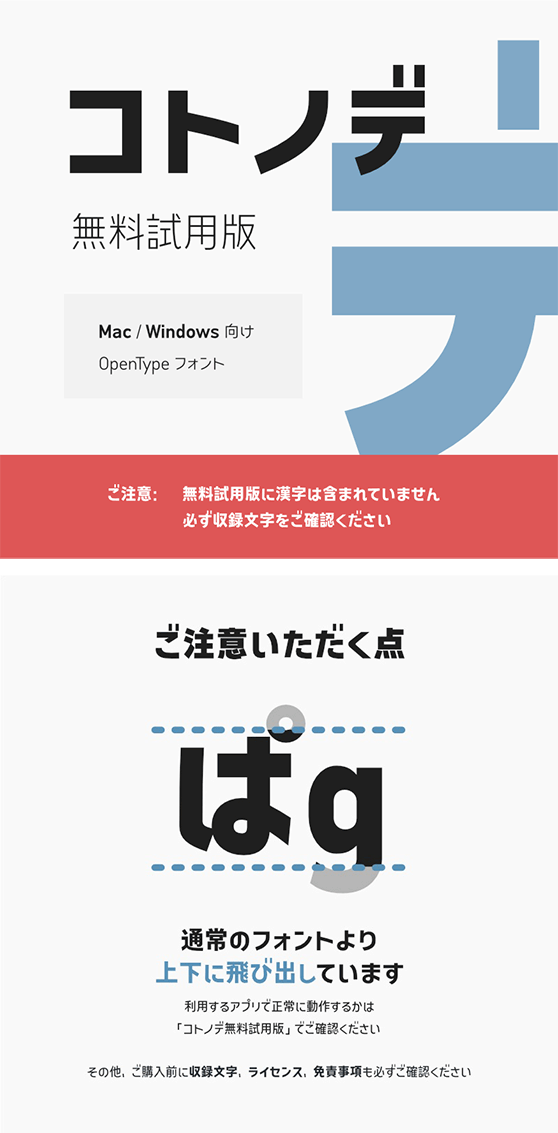
コトノデ無料試用版 Kw-N Black
Kotonode-Black-Muryou-Shiyou-Kw-N
コトノハワークスのフォントは、デザインの都合上、上下に幅があります。利用したいアプリで正常に表示できるかどうかは、こちらのフォントでお試しいただけます。「g」や「ぱ」などの文字でご確認ください。
通常のフォントより上下に飛び出しているデザインのため、ご利用のアプリによっては見切れる場合があることを、ご了承ください。
ひらがな・カタカナ・アルファベット・数字・一部の記号
無料使用版に漢字は含まれていません